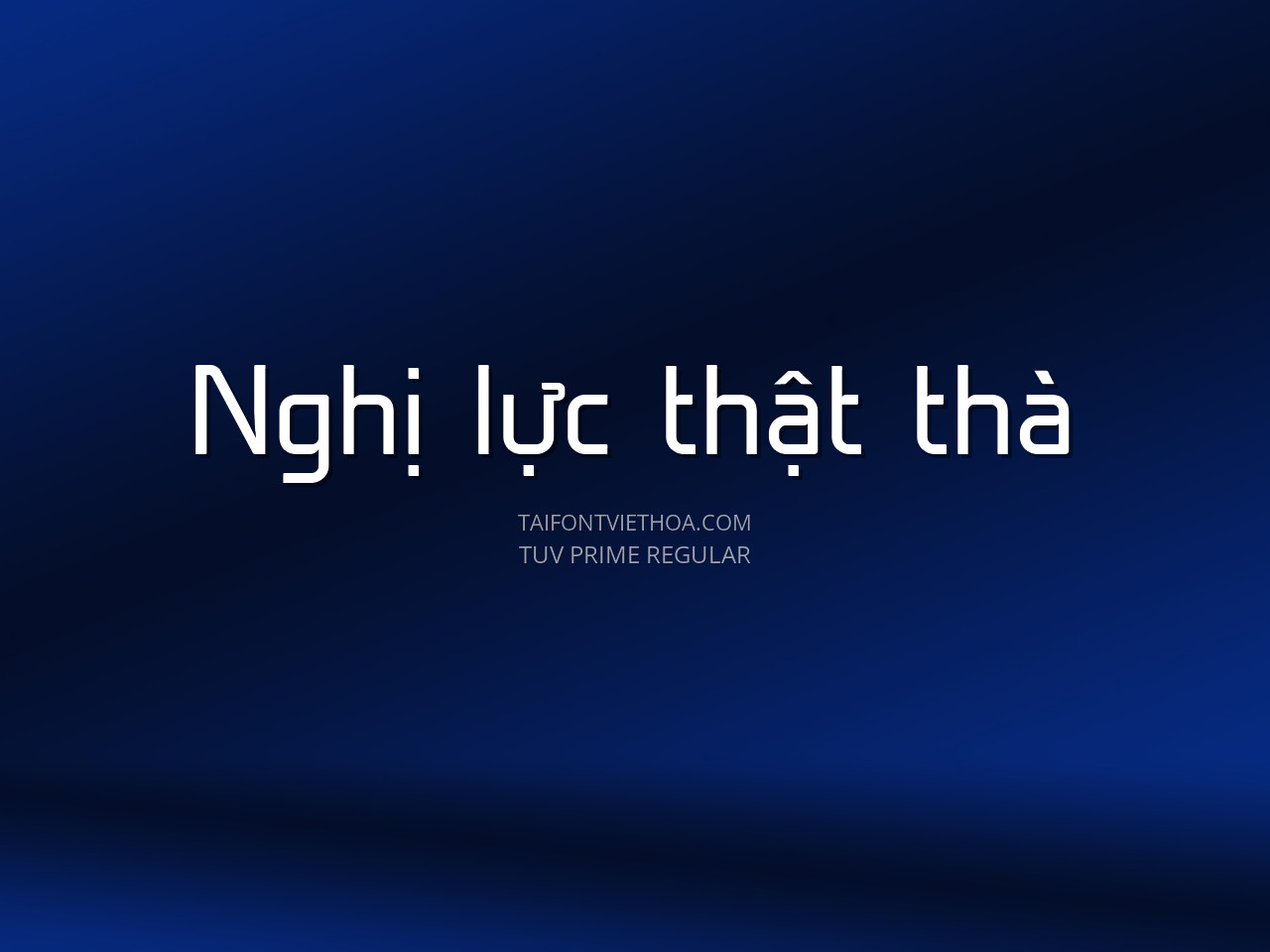
Font việt hóa TUV Prime Regular
Giới thiệu về font TUV Prime Regular – Kiểu chữ sans-serif hiện đại, tinh tế và dễ đọc
TUV Prime Regular là một font sans-serif mang phong cách hiện đại, tinh tế và rất dễ đọc. Font được thiết kế với các nét chữ mềm mại, cân đối và rõ ràng, phù hợp cho các dự án thiết kế thương hiệu, giao diện người dùng và truyền thông kỹ thuật số.
Font TUV Prime Regular đã được việt hóa kỹ lưỡng, hỗ trợ đầy đủ dấu tiếng Việt cùng nhiều ngôn ngữ khác, giúp các nhà thiết kế dễ dàng áp dụng trong nhiều dự án đa dạng mà vẫn giữ được phong cách chuyên nghiệp và thân thiện.
Thiết kế sans-serif mềm mại – Ứng dụng đa dạng trong thương hiệu và giao diện
TUV Prime Regular sở hữu các nét chữ mềm mại, tròn trịa và cân đối, tạo cảm giác thân thiện và dễ tiếp cận. Font phù hợp sử dụng cho tiêu đề, đoạn văn bản, logo và các ấn phẩm quảng cáo, giúp tăng tính thẩm mỹ và sự dễ đọc trong thiết kế. Phong cách trẻ trung của TUV Prime Regular rất thích hợp với các dự án công nghệ, giáo dục, thương mại điện tử và truyền thông.
Ứng dụng lý tưởng: thiết kế nhận diện thương hiệu, website, brochure, tài liệu quảng cáo, giao diện người dùng và các sản phẩm kỹ thuật số. Ngành nghề phù hợp: công nghệ, giáo dục, thương mại điện tử, dịch vụ sáng tạo và startup.